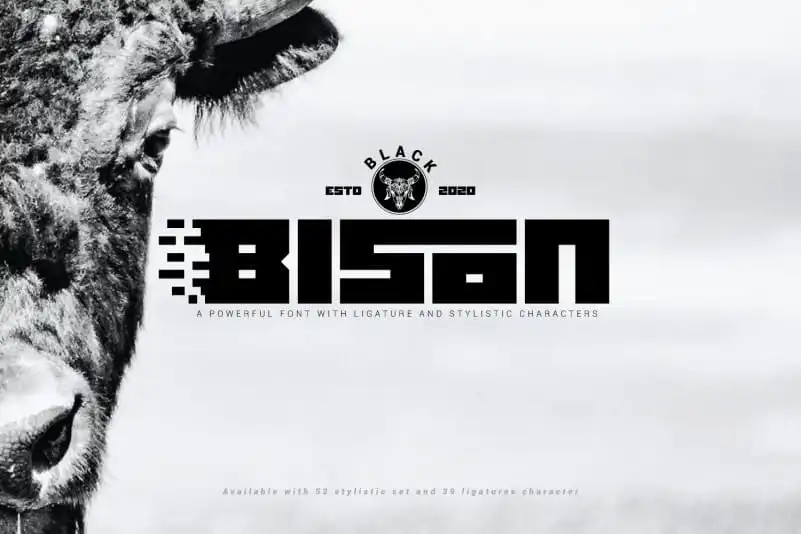
Black Bison Display Font – Download Grátis
Black Bison Display Font é uma família de fontes serifadas única, forte e versátil. Com alternâncias e ligaturas para criar uma exibição visualmente atraente e impactante, essa fonte é perfeita para aplicativos que exigem destaque e sofisticação. Seja para marcas ou nomes comerciais, Black Bison Display Font permite você construir mensagens memoráveis e altamente distintivas. Combinando características de serifadas robustas com alternativas e ligaturas, esta fonte oferece uma maneira perfeita de expressar seu design, sejam eles projetos de marca, materiais de marketing ou outros aplicativos visuais que exigem destaque. Ideal para aqueles procurando por um toque de sofisticação moderna em seus designs, Black Bison Display Font não decepcionará.
Designer: ari